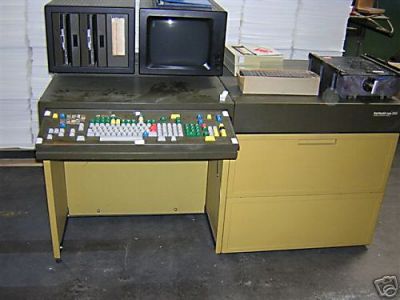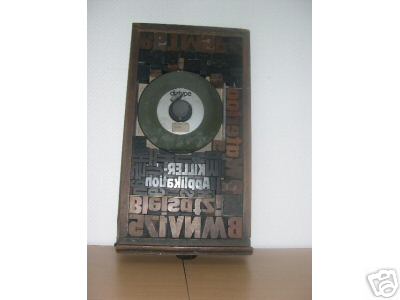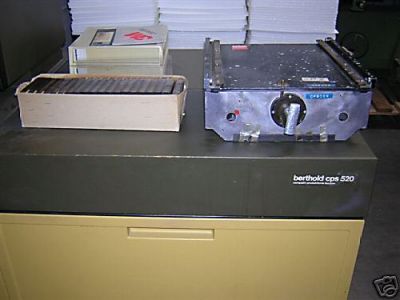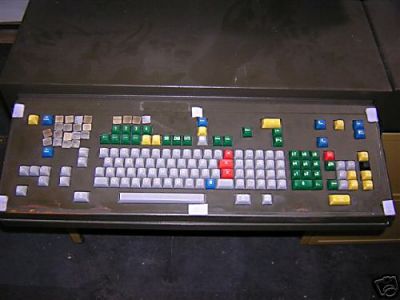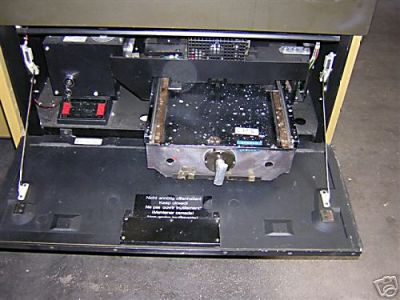
Bleisatz-Zeilengußmaschine Diatype
Das sollten wir vielleicht einmal gemeinsam korrigieren.
Ich habe es mir überlegt:
Sofern sich hier ein Kollege findet, dem ich einen von mir zu schreibenden Text zum Stichwort "Bleisatz" schicken kann und der diesen Text dann entsprechend formatiert und ins Typowiki-Dings einstellt, bin ich bereit, dieses Lapsus unter dem Link zu korrigieren.
Das ist ein Diatype-Gerät:
So ziemlich eines der ersten funktionierenden Fotosatz-Geräte in den Druckvorstufen-Abteilungen von Druckereien.
Im oberen Teil befand sich eine Kassette mit lichtempfindlichem Material, Film oder auch Papier. Links an dem Schalter bewegte man sich innerhalb der vorn befestigten Schablone nach oben und unten und fuhr so mit dem Revolvergriff die Position des zu belichtenden Zeichens an und löste die Belichtung dann über den Knopf am Griff aus.
Nach der Belichtung ging man mit der geschlossenen Kassette in die Dunkelkammer, holte das belichtete Material heraus und schob's in die Entwicklungsmaschine. Fertig. Dolle Sache.
Wie Ihr vielleicht bemerkt: Es gab keinen Display. Und auch keine Möglichkeit, die Satzarbeit abzuspeichern. Also ein mechanisches System.
Auf diesem Gerät haben Fotosetzer früher nicht nur Zeilen abgesetzt, sondern auch z.B. Tabellen mit geteilten Tabellenköpfen und teilweise auch komplizierte Akzidenzen. Man hatte immer den Ehrgeiz, eine Satzarbeit fertig auf Stand zu belichten, ohne in der Montage nachzuarbeiten. Also hing zunächst einmal alles von einer sehr sorgfältigen AV ab.
Spannend wurde es, wenn's ans Setzen ging.
- Radio aus.
- Bescheid geben: nicht stören.
- Tür zu.
Und dann setzte man vor sich hin. Das größte Problem war nämlich, wenn dann doch irgendjemand störte und hereinplatzte. Egal, was es war und wie kurz es dauerte: Man wußte dann nicht mehr, ob man die Belichtung des letzten Zeichens schon ausgeführt hatte oder nicht.
Und dann schlug immer Murphy's Stunde (Deppen-Apostroph wegen des englischen Eigennamens): Belichtete man, gab's eine Doppelbelichtung. Belichtete man nicht, fehlte was.
Dieses Ding konnte einen rasend machen.
Aber es als Bleisatz-Zeilengußmaschine zu bezeichnen, ist nun auch nicht richtig.
Ich hab's mal "Killer-Applikation" genannt. Weil's der Einstieg in den Aussteig aus dem Bleisatz darstellte. Hier verarbeitet wurde eine original Diatype-Scheibe, auf der sich die negativen Zeichen einer jeden Schrift befanden:
Ich kann gern einen Artikel von Dir einstellen. Der Artikel ist ja im Augenblick leider - vom Fehler ganz zu schweigen - etwas dürftig. Vielleicht magst Du auch einen Artikel zur Diatype schreiben? Den stellte ich auch gern formatiert ins Wiki. Ich habe hilfsweise, bis Du dazu kommst etwas besseres zu schreiben, im Bleisatz-Artikel »Diatype« durch »Linotype« ersetzt und den Linotype-Artikel entsprechend ergänzt, magst Du da evtl. auch kurz drüberlesen?
Man wußte dann nicht mehr, ob man die Belichtung des letzten Zeichens schon ausgeführt hatte oder nicht.
wurden dann beim setzen/belichten die bereits gesetzten buchstaben vom manuskript gestrichen oder wie kannman sich das vorstellen?
brrr. kein job für mich ...
Ich kann gern einen Artikel von Dir einstellen. Der Artikel ist ja im Augenblick leider - vom Fehler ganz zu schweigen - etwas dürftig. Vielleicht magst Du auch einen Artikel zur Diatype schreiben? Den stellte ich auch gern formatiert ins Wiki. Ich habe hilfsweise, bis Du dazu kommst etwas besseres zu schreiben, im Bleisatz-Artikel »Diatype« durch »Linotype« ersetzt und den Linotype-Artikel entsprechend ergänzt, magst Du da evtl. auch kurz drüberlesen?
Philipp
Was hältst Du denn davon, wenn wir beide ein Typowiki-Projekt "Bleisatz" beginnen?
Ich würde zunächst einmal innerhalb einer Woche einen ausführlichen Artikel über Bleisatz schreiben. Und von diesem ausgehend, könnten wir dann gemeinsam zwei bis drei neue Artikel jeweils schreiben, formatieren und hochladen. Das ginge sicher dann auch in die Fotosatz-Schiene rein. Vielleicht bekämen wir ja sogar noch in diesem Bereich andere dazu, etwas hinzuzufügen.
Wenn wir es auf diese zwei bis drei Beiträge pro Woche belassen, hätten wir bis Jahresende schon mal einen ganz guten Grundstock.
Man wußte dann nicht mehr, ob man die Belichtung des letzten Zeichens schon ausgeführt hatte oder nicht.
wurden dann beim setzen/belichten die bereits gesetzten buchstaben vom manuskript gestrichen oder wie kannman sich das vorstellen?
brrr. kein job für mich ...
Man muß es aus der Zeit heraus verstehen.
Gemessen an der Zeit, die man im Bleisatz brauchte - und das war ja die einzige und auch bewährte Methode - hat man trotz der umfangreichen AV und der möglichen Nachkorrektur sehr viel schneller und natürlich auch qualitativ sehr viel höherwertiger setzen können.